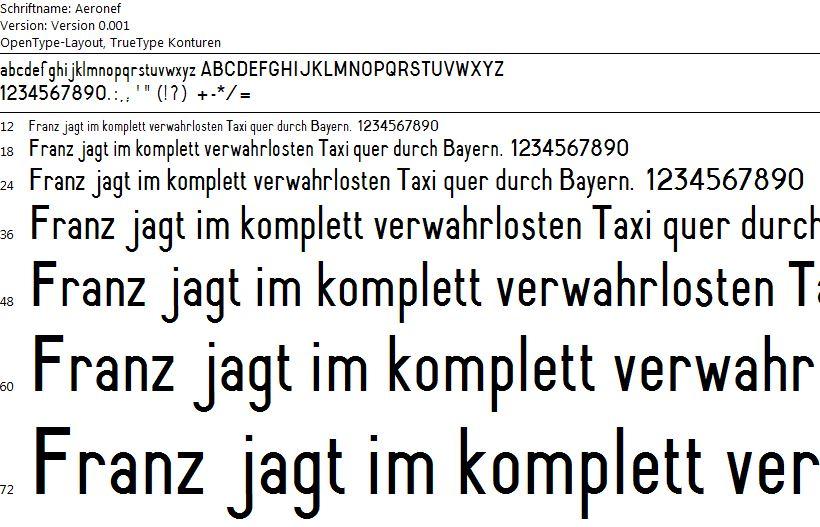
Gibt es eine passende Schriftart zu der Vorschrift NF L80-090?
ich habe die französische Vorschrift NF L80-090 vor mir liegen. Bei dieser Vorschrift ist jeder Buchstabe, Ziffer und jedes Zeichen von der Größe und den Proportionen genau definiert.  Wenn man jetzt z.B. ein Wort bilden will, muss man zuerst die einzelnen Buchstaben im Grafikprogramm zeichnen und dann zusammensetzen. Das wird bei vielen Wörtern natürlich extrem aufwändig.
Meine Frage: Ist für die Vorschrift NF L80-090 eine Schriftart vorhanden, mit der man den Text über die Tastatur eingeben kann?
Ich bin mir eigentlich ziemlich sicher, dass es da eine Schriftart geben muss, handelt es sich ja um etwas vergleichbares, wie die deutsche DIN 1451, nur eben für die Anschriften auf Luftfahrzeugen.
Wie diese Schriftart jetzt aber heißt, glaube ich, weiß keiner hier. Ich kenne aber einen zwar mittlerweile verrenteten Ingenieur der Airbus-Industrie, deren Zentrale ja bekanntlich in Toulouse sitzt, und die ja bekannter weise Luftfahrzeuge produzieren, und demzufolge auch Anschriften, bestimmt nach dieser Norm darauf anbringen. Ich weiß nicht, ob ich den schnell erreiche, aber ich werde ihn bitten, bei seinen ehemaligen Kollegen danach zu fragen. Vielleicht haben wir ja Glück.
Falls nicht, könnte ich höchstens anbieten, solch einen Font anzufertigen - würde ja in mein Normschriften-Portfolio passen :-) allerdings werde ich mir dazu ungern die 45,60, die der Beuth-Vertrieb für das Normbatt verlangt ans Bein binden, da hoffe ich auf Verständnis.
Vielleicht kann die Frage jemand auf einem Forum für Sportfliegerei beantworten. Leider scheint diese „Norm“ kostenpflichtig zu sein. Stimmt das? Liegen die Zeichen überhaupt als Dateien vor oder müssen sie tatsächlich gezeichnet werden? Hört sich so an, als seien die Proportionen und Größenverhältnisse zwar vorgegeben, aber die eigentlichen Formen nicht klar definiert.
anbei die Vorschrift, die auf Französisch ist :-(
@Arno Enslin: Die Zeichen müssen so wie es scheint leider alle gezeichnet werden, falls es keinen Font gibt.
Wenn man jetzt z.B. ein Wort bilden will, muss man zuerst die einzelnen Buchstaben im Grafikprogramm zeichnen und dann zusammensetzen. Das wird bei vielen Wörtern natürlich extrem aufwändig.
Die Zeichen zu zeichnen, ist aber weit aufwändiger, als aus den fertigen Zeichen einen Font zu machen. Die Sache wird also nicht mit zunehmender Anzahl der Wörter aufwändiger. Mit zunehmender Anzahl der Wörter (zufällig ausgewählt) steigt nur die Wahrscheinlichkeit, dass du alle Zeichen brauchst. Ich würde meine Suche ausdehnen: Also nicht nur nach einem fertigen Font suchen, sondern nach einem Container mit Bitmap- oder Vektordateien. Ein PDF, in das solche Dateien eingebettet sind, ginge auch.
Okay...oder man zeichnet alle Zeichen und lässt dann daraus einen Font erstellen. Ich weiß nicht, wo ich Zeichen nach der NFL80-090 finden soll.
Stimmt, aber ich bräuchte die Schriftart zum Drucken.
Bei der pdf. sind die Rundungen "gezackt", ich denke, da es eine Gravurschrift ist.
Ich hab mir auch die PDF angeschaut, das ist rtecht ungeeignet, daraus einen Font zu bauen, da diese CAD-Typisch je nach Größe der Darstellung in Geradenabschitte aufgelöst wird.
Also warte ich noch ein wenig auf die Rückmeldung meines Freundes, der ja Ing bei der Airbus.Industrie wasr, die sicher diese Schrift auch verwenden dürften, ob er da Informationen beitragen kann.
Sonst ist das ja auch kein  so großes Problem, da ich ja schon ähnliche Normschrifteen umgesetzt habe, schätze ich mal, in ca. 20 Arbeitsstunden einen sorgfältig gezeichneten Font auf die Füße zu stellen, schließlich sind hier fa auch die Vor- und Nachbreiten genormt, sodass ein Kerning wohl eher wenig Arbeit macht, und eine Nutzung in kleiner Größe am Bildschrim,. was einiges an Arbeit für ein sauberes Hinting wäre, wohl auch nicht in Betracht kommt. Auto-Hinting dürfte hier ausreichen.
@catfonts: Hört sich gut an. Es geht um einen potenziellen Auftrag bei Airbus über Aufkleber in verschiedenen Größen, bei der man diese Schriftart verwenden muss. Wenn unsere Firma den Auftrag erhält, können wir über die Anfertigung des Fonts reden. Das Bieterverfahren läuft allerdings noch bis Mitte Januar 2017 :-)
Mmh. Kannst du dann nicht direkt euren potentiellen Auftraggeber fragen, ob er die Schrift als Font oder Grafik-Paket hat und euch zur Verfügung stellt?
Auto-Hinting dürfte hier ausreichen.
Aaaa - ha! So ist die sache mit dem kleinen l:
Innerhalb eines Wortes (inclus dans un mot) wird das gerade l, also der einfache Strich verwendet,
alleinstehend (solo) dann das l mit Häkchen, z.B. als Einheitenzeichen für Liter.